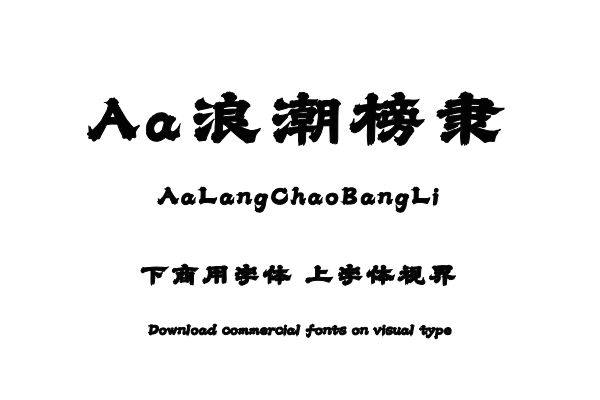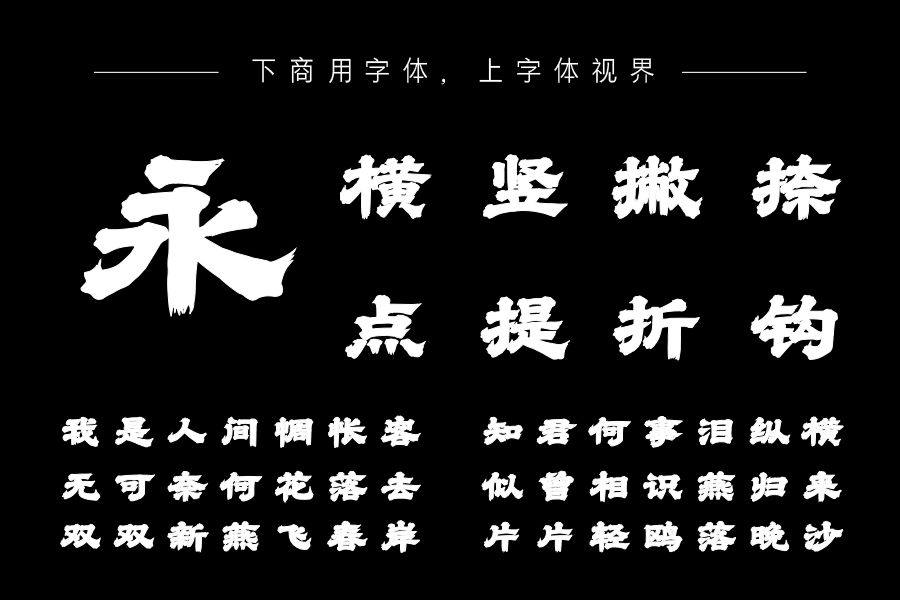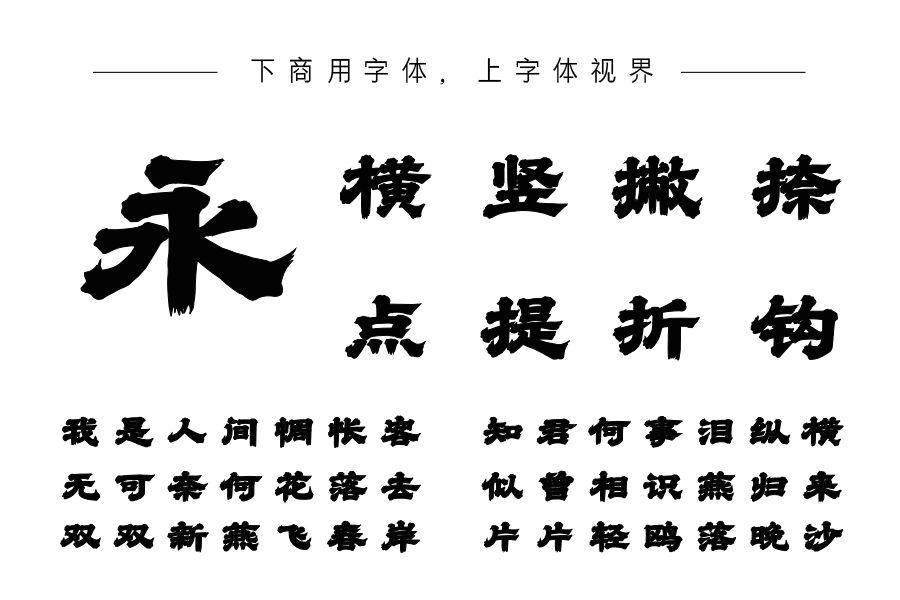
本字体用数码笔刷书写,脱胎于传统隶书的古朴沉静,起收笔顿挫有力、笔锋夸张、飞白丰富,粗重醒目、视觉张力强,适合国潮、中餐、快消等行业推广品牌与产品。购买须知:“下载服务费”与“字体VIP”所获得字体 仅用于个人非商用, 商用请联系付费授权。本字体为电脑用字,手机没有root权限不支持直接手机换字(手机如何root,请自行百度搜索教程)。购买前请先 了解清楚后再付款 ,字体为虚拟产品无法回收 一旦购买不支持退款。